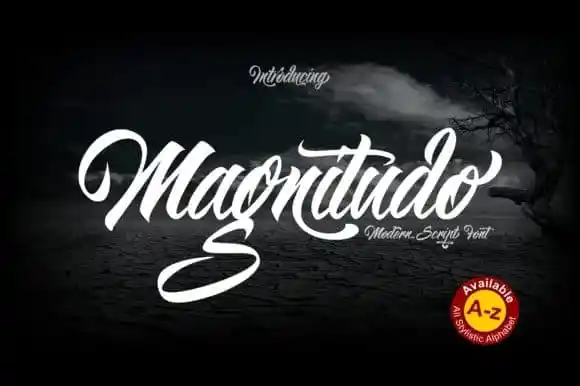
Magnitudo Script Font – Fonte Grátis
Magnitudo Script Font
Magnitudo Script Font é uma nova adição à galera de tipos script que traz uma experiência única e cativante para os projetos DIY. Escrevida através de movimentos suaves com a ajuda de um especializado pen, essa tipografia moderna parece genuinamente autêntica graças ao seu equilíbrio perfeito entre um canetão e um lápis. Desenhada pelo talentoso designer ZetDesign na plataforma 99designs, Magnitudo captura o encanto de uma escrita manual enquanto oferece a sofisticação moderna que tanto procuramos em nossos projetos digitais. Esta fonte traz uma sensação de conforto e familiaridade ao seu trabalho, mas também eleva-o à próxima nível. É perfeito para personalizar seus produtos finais ou criar gráficos altamente pessoais e reconhecíveis. Sua textura única e detalhes cuidadosos o tornam um instrumento valioso para qualquer designer que busca expressar suas ideias de maneira autêntica e emocionante. Com Magnitudo, você não só pode diferenciar seu trabalho entre outros, mas também pode transmitir uma mensagem de confiança e comprometimento. Sem dúvida, é a escolha perfeita para aqueles que valorizam tanto o estilo quanto a funcionalidade em suas tipografias. Engane-se se pensar que Magnitudo Script Font só deve ser usada no papel – com seu charme e versatilidade, você encontrará inúmeras maneiras de aplicá-la digitalmente.